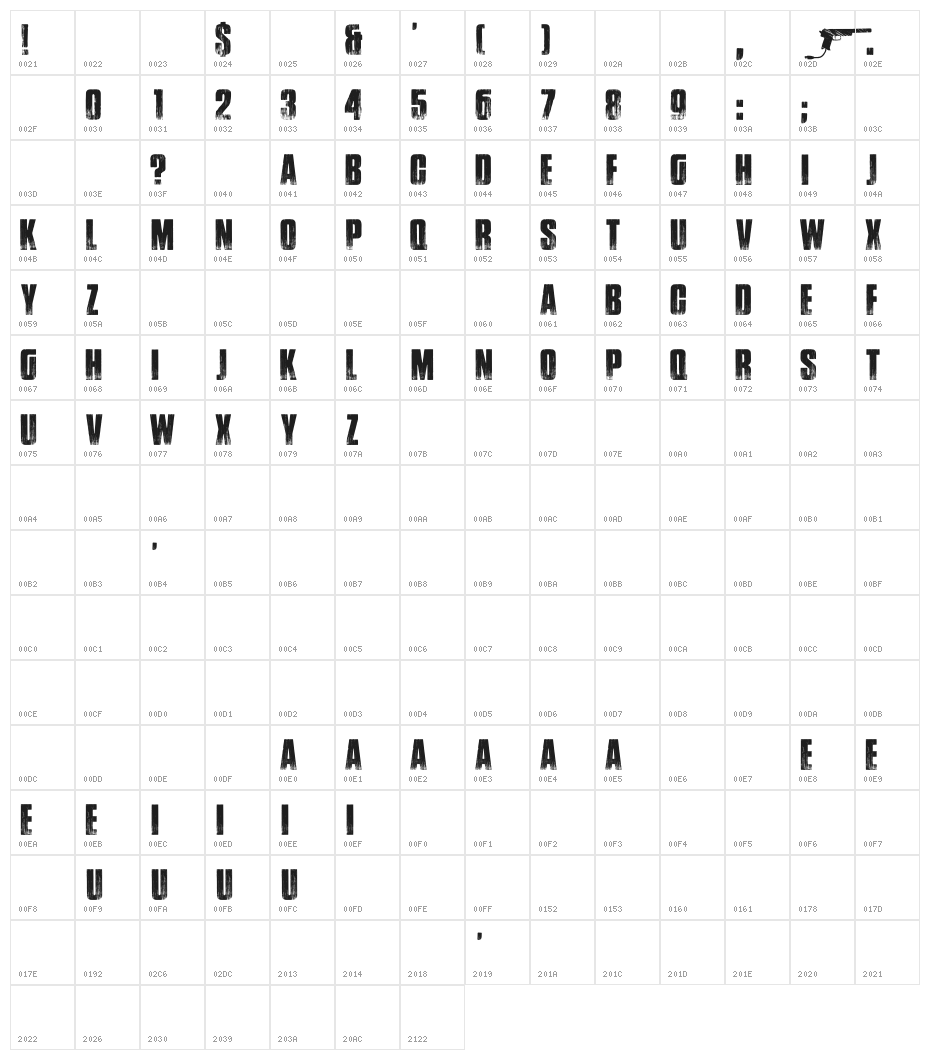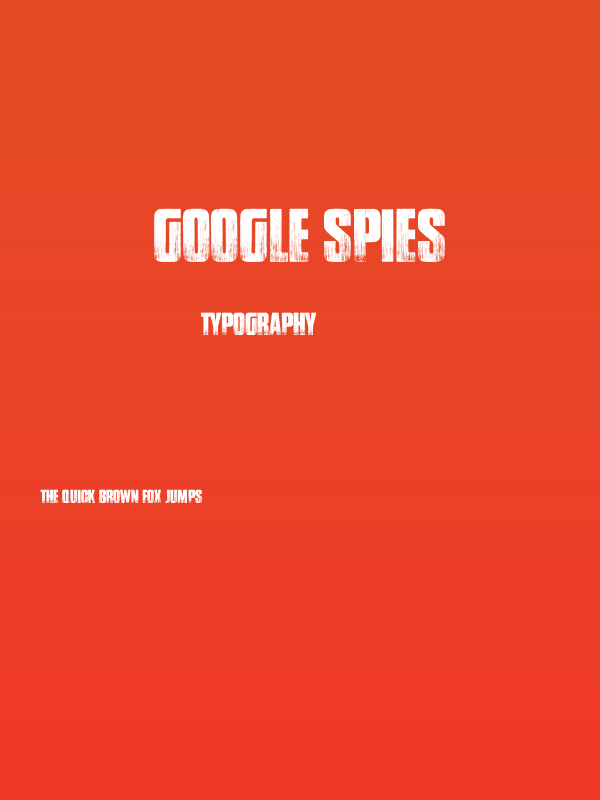
Google spies Font
✎ Distorted Eroded
| Categorie | Distorted Eroded |
| Stile generale | Vintage, Grunge |
| Progetti proposti | Ideal for posters, album covers, branding for edgy products, or any design needing a grunge or vintage touch. |